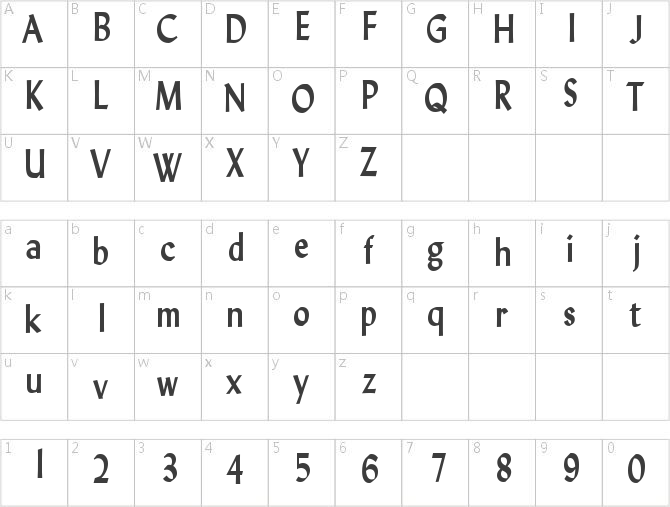
Lynda-Condensed-Bold 詳情頁
字體名稱: Lynda-C
Lynda-Condensed-Bold
Lynda-Condensed-Bold字體字庫是一款讓人賞心悅目、百看不厭的英文字體,適合各類廣告和產品包裝設計應用,字體大小0.05MB,格式為ttf字體,上傳用戶是東方時尚,作者/版權方為未知